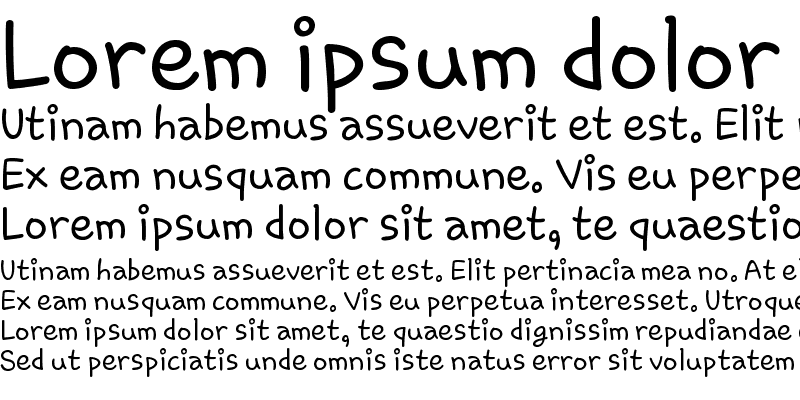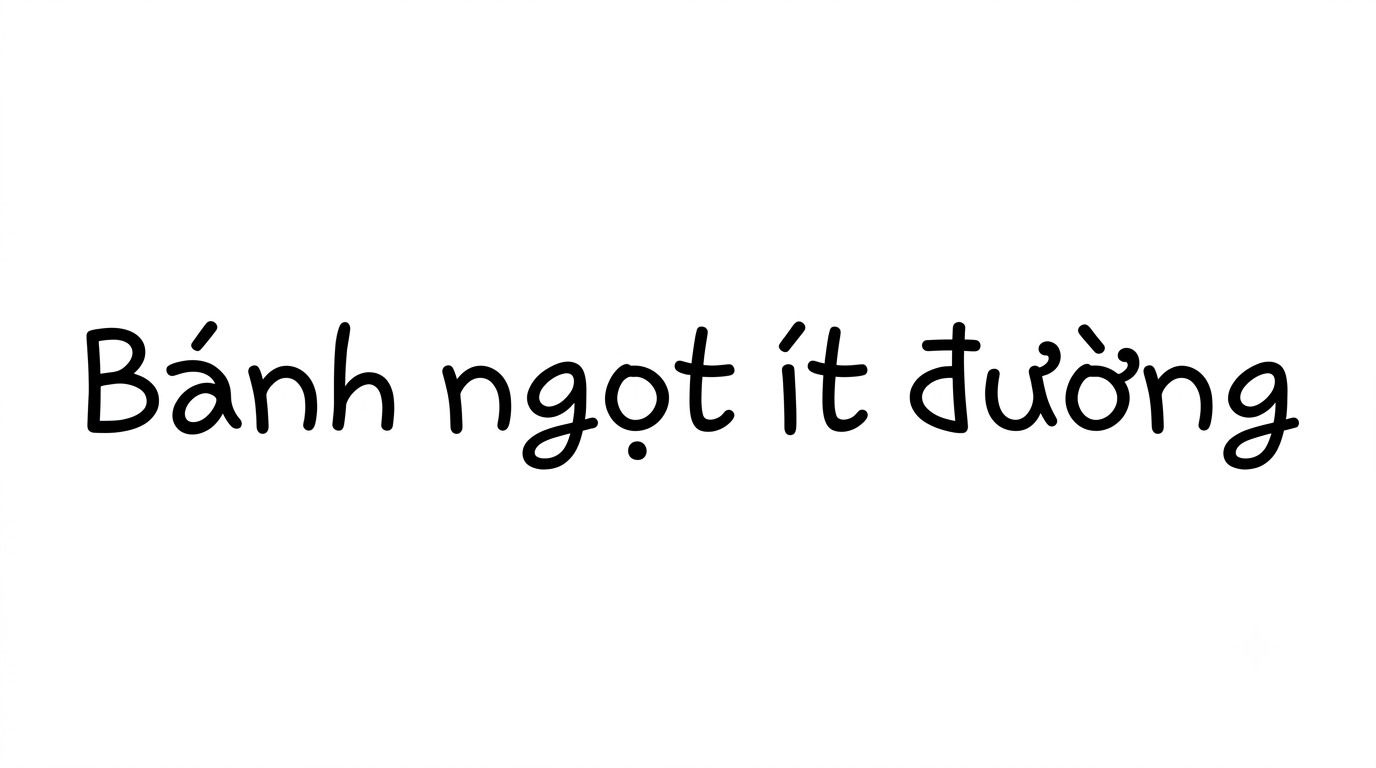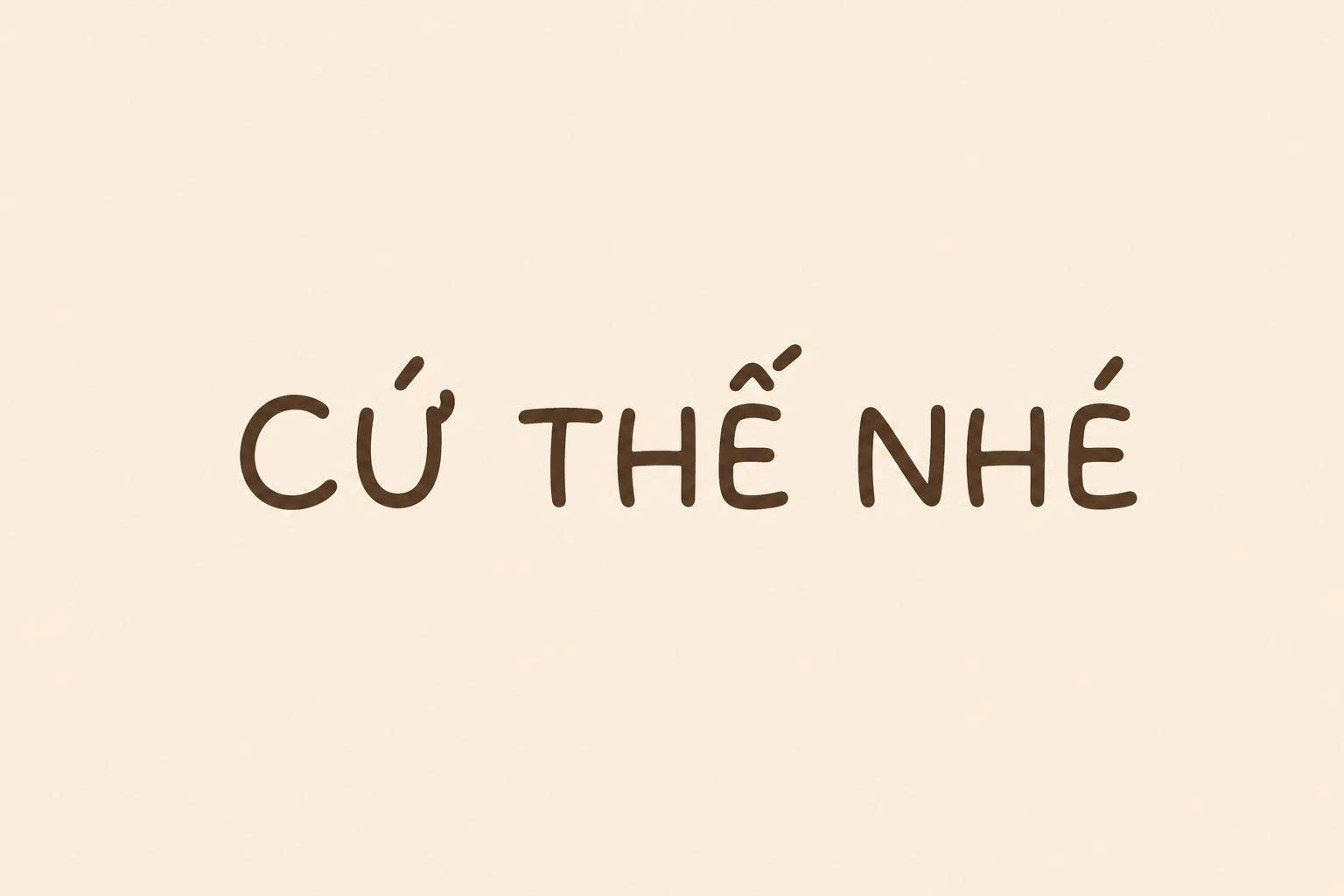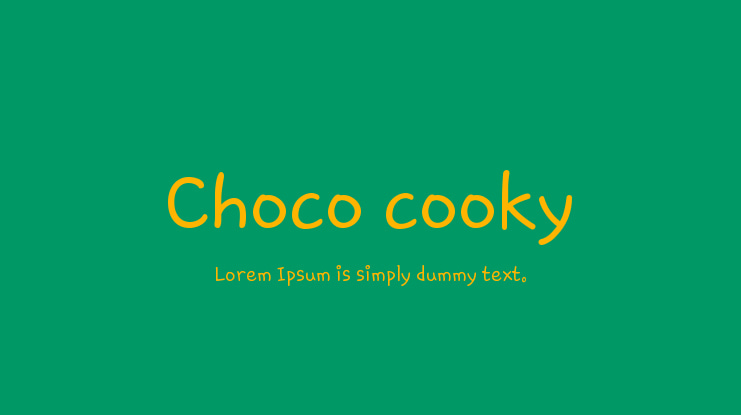
Font Chococooky Việt hóa là bộ phông chữ thuộc dòng Casual Handwritten nổi tiếng toàn cầu gắn liền với giao diện điện thoại thông minh Samsung, mô phỏng sinh động nét chữ viết tay tròn xoe, ngọt ngào như những chiếc bánh quy sô-cô-la nướng giòn. Với vẻ ngoài đáng yêu, ấm áp và giàu năng lượng tích cực, font chữ Chococooky là chất liệu trực quan tuyệt vời để các kiến trúc sư, nhà thiết kế mang lại sự tươi vui cho các bản vẽ phối cảnh tiệm bánh ngọt container, quầy trà sữa lưu động hay góc sinh hoạt gia đình trong nhà lắp ghép.
Nét vẽ tròn trịa thơm thảo và cảm xúc gần gũi của font Chococooky Việt hóa
Điểm cuốn hút của font Chococooky Việt hóa nằm ở cấu trúc hình thể bo cong tự nhiên ở mọi góc nét, loại bỏ hoàn toàn cảm giác sắc nhọn hay sự khô cứng của các phông chữ in ấn công nghiệp. Từng con chữ sở hữu độ nghiêng nhẹ ngẫu hứng và tỷ lệ mập mạp vừa vặn, mang lại cảm giác thân thương như những mẩu giấy nhắn viết tay kẹp trên cánh cửa tủ lạnh gia đình.
Sự ổn định về mặt cảm xúc của dòng font này giúp khơi gợi niềm vui, sự mến khách và bầu không khí sum vầy đầm ấm. Khi kết hợp cùng các vật liệu kiến trúc thân thiện như gỗ thông vàng sáng, tường panel sơn màu kem sữa, kính trong suốt hay gạch thẻ màu pastel trong các căn nhà lắp ghép nghỉ dưỡng, Chococooky tạo nên sự hòa quyện thẩm mỹ vô cùng ngọt ngào.
| Phân loại phong cách | Casual Handwritten / Rounded Cute / Bakery Display |
| Mục đích phù hợp | Menu tiệm bánh, biển tên homestay gia đình, poster |
Tư vấn từ chuyên viên: Chococooky sở hữu nét tạo hình tròn trịa và giàu cảm xúc trẻ thơ. Để bản thiết kế đạt hiệu quả thẩm mỹ tốt, bạn nên sử dụng phông chữ này cho các tiêu đề thực đơn, tên góc chức năng hoặc các câu khẩu hiệu ngắn.
03 Ứng dụng font chữ Chococooky vào công trình thực tế
Nhờ vẻ ngoài ngộ nghĩnh và tính gợi cảm xúc ấm cúng, bộ phông chữ này mang lại giá trị thực tế lớn trong khâu tạo điểm nhấn cho các công trình hiện đại:
- Bảng thực đơn và Biển tên quầy Bar Tiệm Bánh Container: Những nét chữ tròn xoe của Chococooky rất ăn ý khi gia công chữ nổi bằng mica màu nâu socola hoặc dán decal trên kính quầy pha chế, mang lại diện mạo ngọt ngào và kích thích vị giác của thực khách ghé thăm.
- Bảng tên phòng và Biển chỉ dẫn Homestay Gia đình: Phông chữ này khi sơn thủ công trên các thanh gỗ thông hoặc bảng gốm nung men sẽ giúp các căn phòng nghỉ dưỡng toát lên chất đồng nội, tạo cảm giác thư thái cho các gia đình có con nhỏ.
- Trang trí góc đọc sách và Không gian phòng ngủ của bé: Bạn có thể dùng font chữ Chococooky để làm bảng nội quy thân thiện, nhãn dán đồ dùng học tập trong căn hộ lắp ghép, tạo cảm giác ngăn nắp và nuôi dưỡng niềm vui học tập của trẻ.
03 Lưu ý bố cục font Chococooky luôn ngọt ngào và dễ nhìn
Để khai thác hiệu quả vẻ đẹp của dòng font viết tay đáng yêu này mà không gây cảm giác lộn xộn cho trang giấy, người thiết kế nên lưu tâm một số kinh nghiệm sau:
- Bố trí khoảng thở tự nhiên: Cấu trúc các ký tự của Chococooky có độ nở tròn về bề ngang. Bạn nên chừa khoảng trống xung quanh tiêu đề rộng rãi để các con chữ có không gian tỏa sáng, tránh việc để các chi tiết đồ họa phụ trợ chèn ép câu chữ.
- Hạn chế viết hoa toàn bộ cụm từ: Việc viết hoa liên tiếp nhiều chữ cái sẽ làm câu văn trông nặng nề và làm giảm đi nhịp điệu nhún nhảy tự nhiên của bộ chữ. Hãy ưu tiên viết thường và chỉ viết hoa chữ cái đầu câu.
- Kết hợp cùng gam màu kẹo ngọt ấm áp: Chococooky phát huy hiệu quả thị giác cao khi phối cùng các tông màu mang sắc thái đồ ngọt như nâu bánh quy, vàng bơ, hồng phấn, kem sữa hoặc xanh bạc hà nhạt trên nền tường sáng.